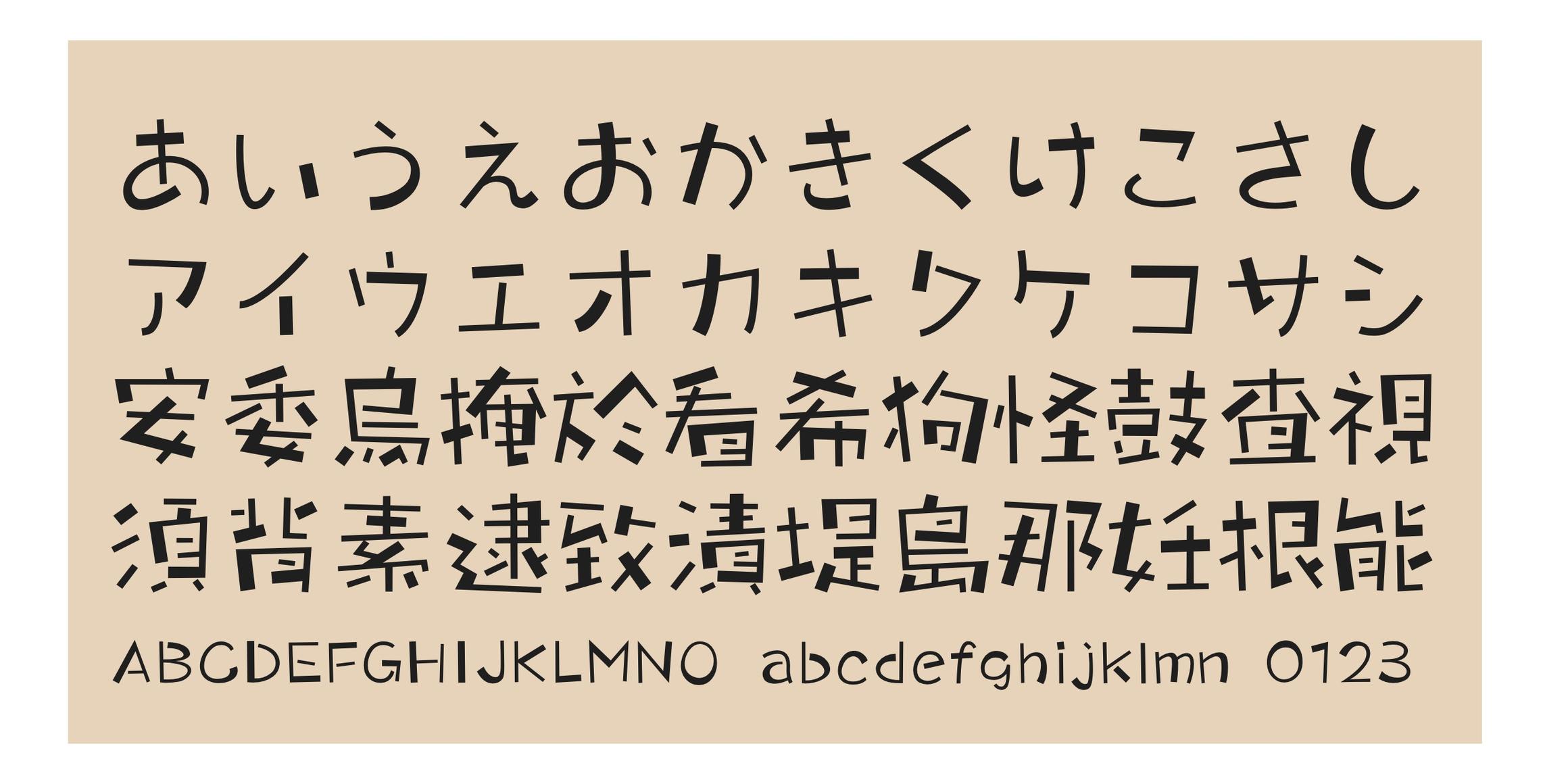
Sandoll 광수들풀
01 Scratch
02 Stamp
03 Beat
산돌 광수들풀은 광수체의 자유로운 모듈과 들풀체의 자연스러움이 어우러진 폰트이다.
잘 알려진 광수체의 자유로운 모듈에 서정적인 들풀체의 이미지를 조합하여 다정하면서도 톡톡 튀는 신선함을 연출하였다.